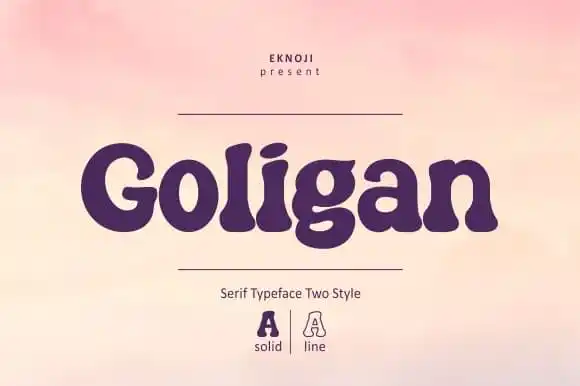
Goligan Display Font – Download Grátis
A Goligan Display Font é uma nova tipografia serifada criada pela Eknoji Studio com características masculinas adequadas para estilos tradicionais ou modernos. Esta fonte é perfeitamente adaptável à combinação com outras tipografias sans-serif, sendo ideal tanto para aplicações em posters, logomarcas, headlines e títulos nas capas de livros, filmes, conteúdo e outros ambientes onde a estética gráfica importa. Suavemente elegante e robustamente forte, Goligan Display é uma escolha conveniente para quando você deseja transmitir confiança e estilo em um design visual. Sempre uma ótima opção para designer de logo ou editor de designs gráficos que estão buscando um estilo sofisticado e moderno, a Goligan Display está disponível para aqueles que desejam adicionar um toque único à sua próxima criação visual.